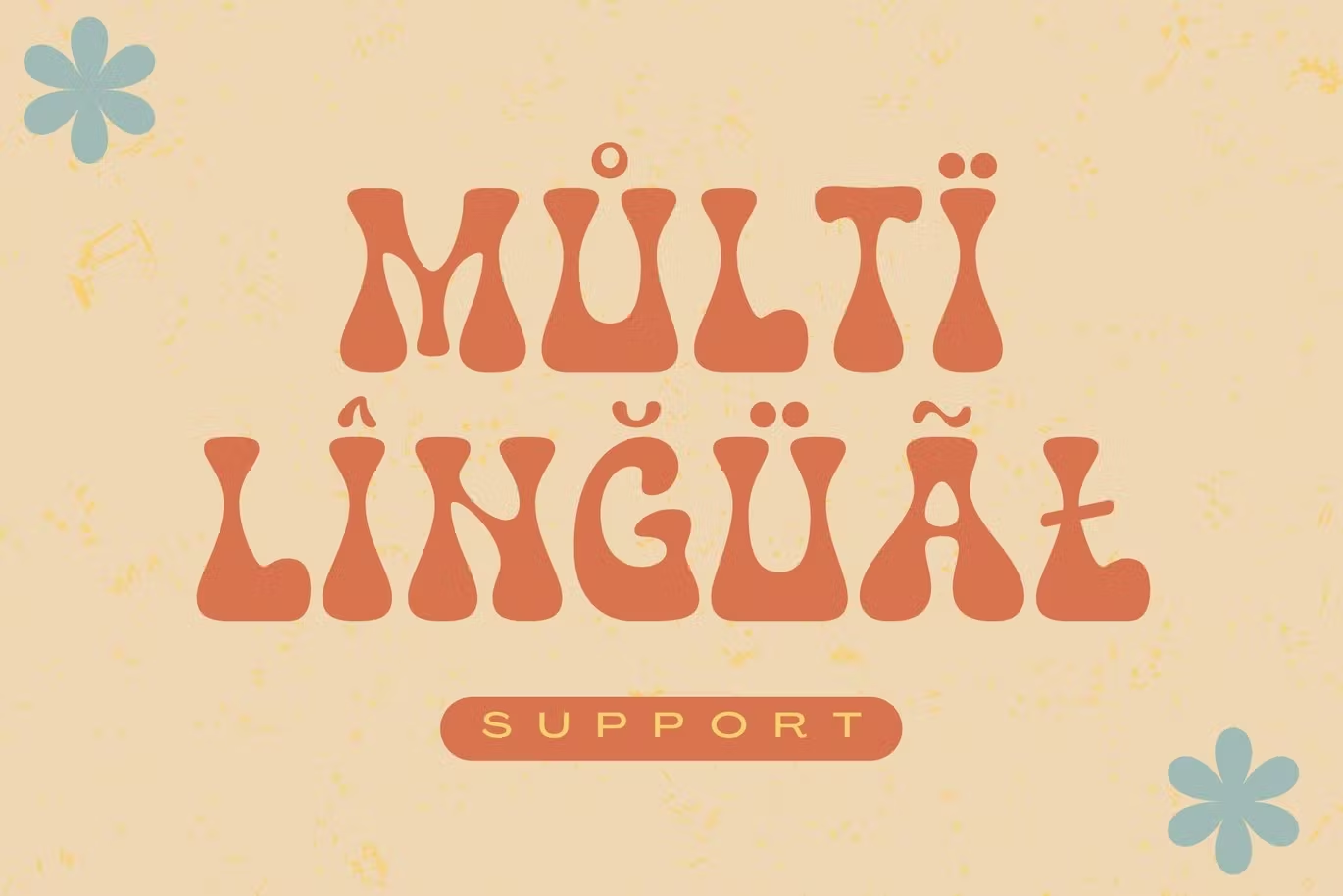
Retro Cool Font
Description de Retro Cool Font
Retro Cool , contemporain de la police Sans empattement,
Retro Cool offre une belle harmonie typographique pour une diversité de projets de conception, notamment des logos et des marques, des publications sur les réseaux sociaux, des publicités et des conceptions de produits.